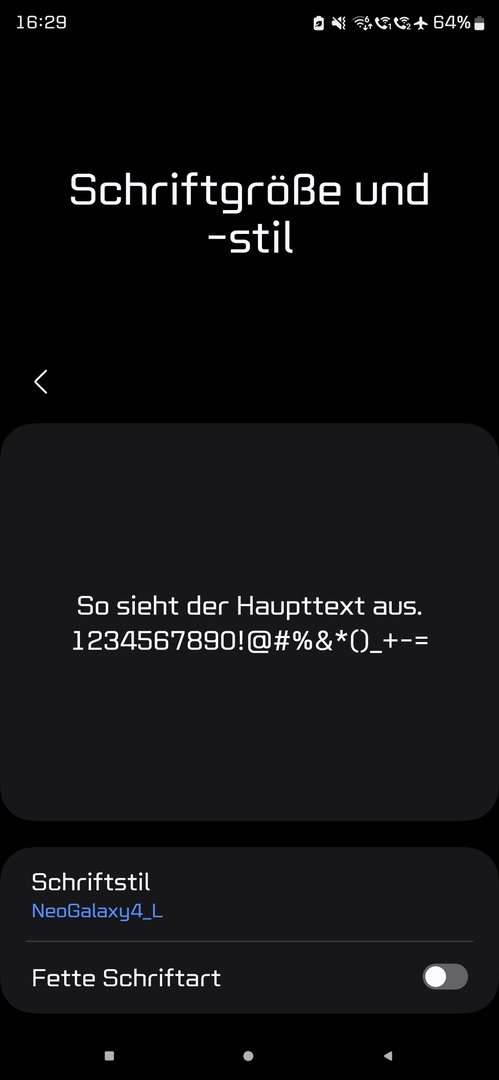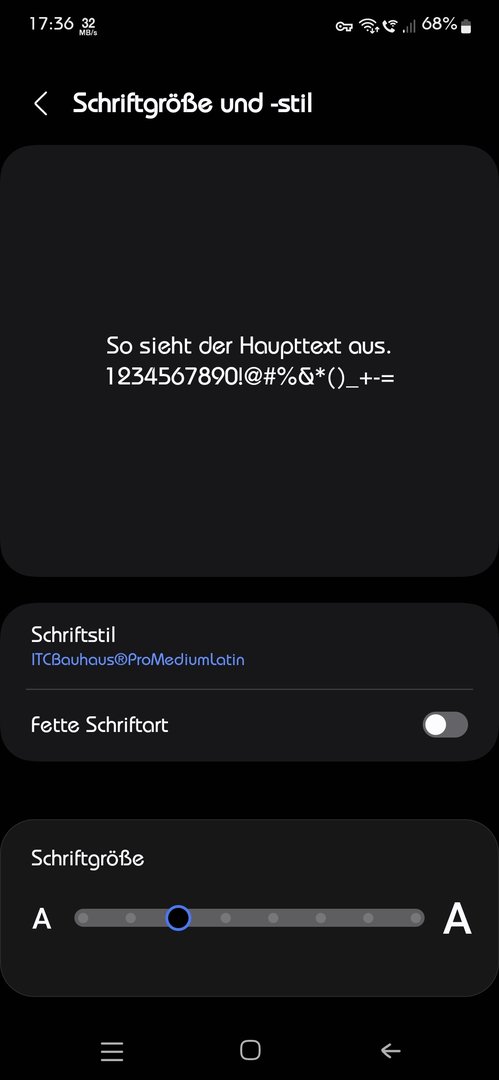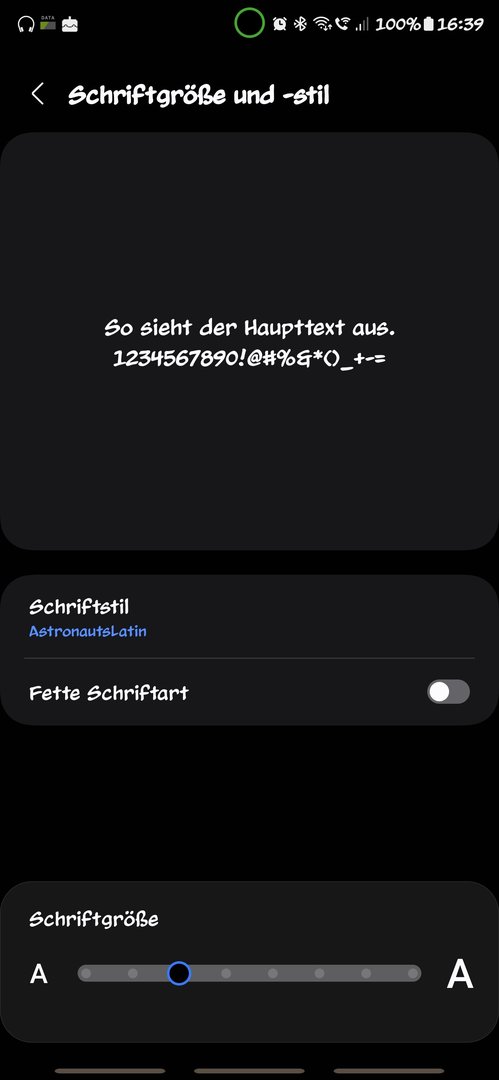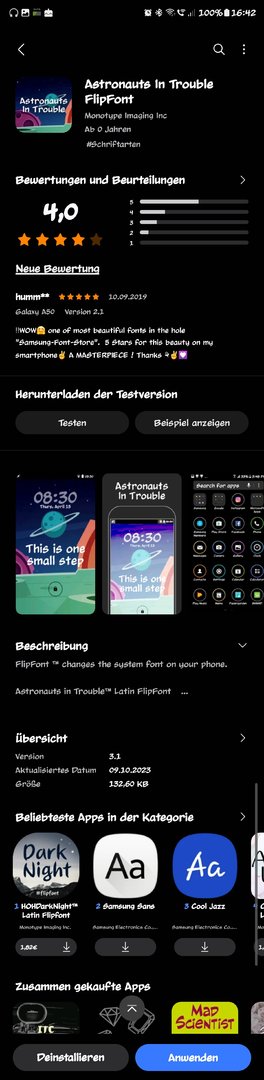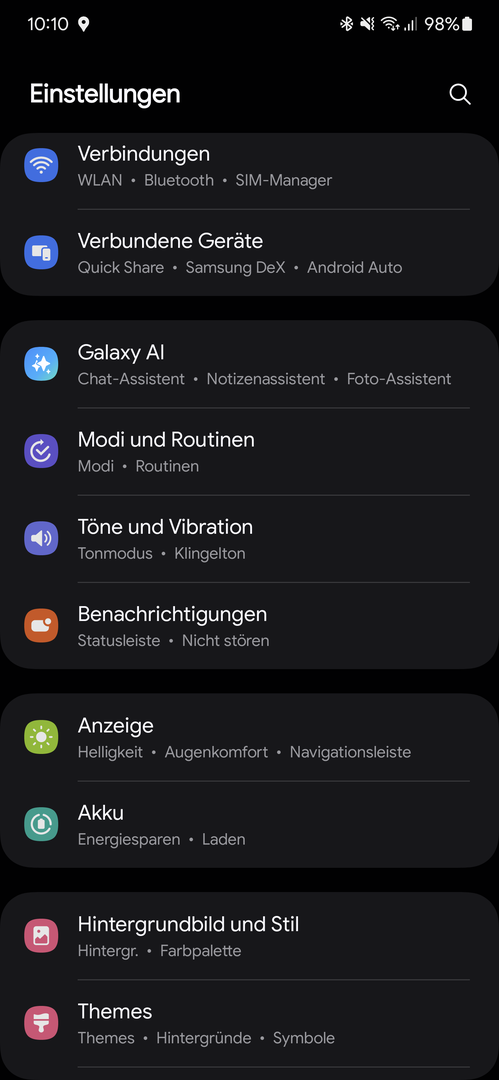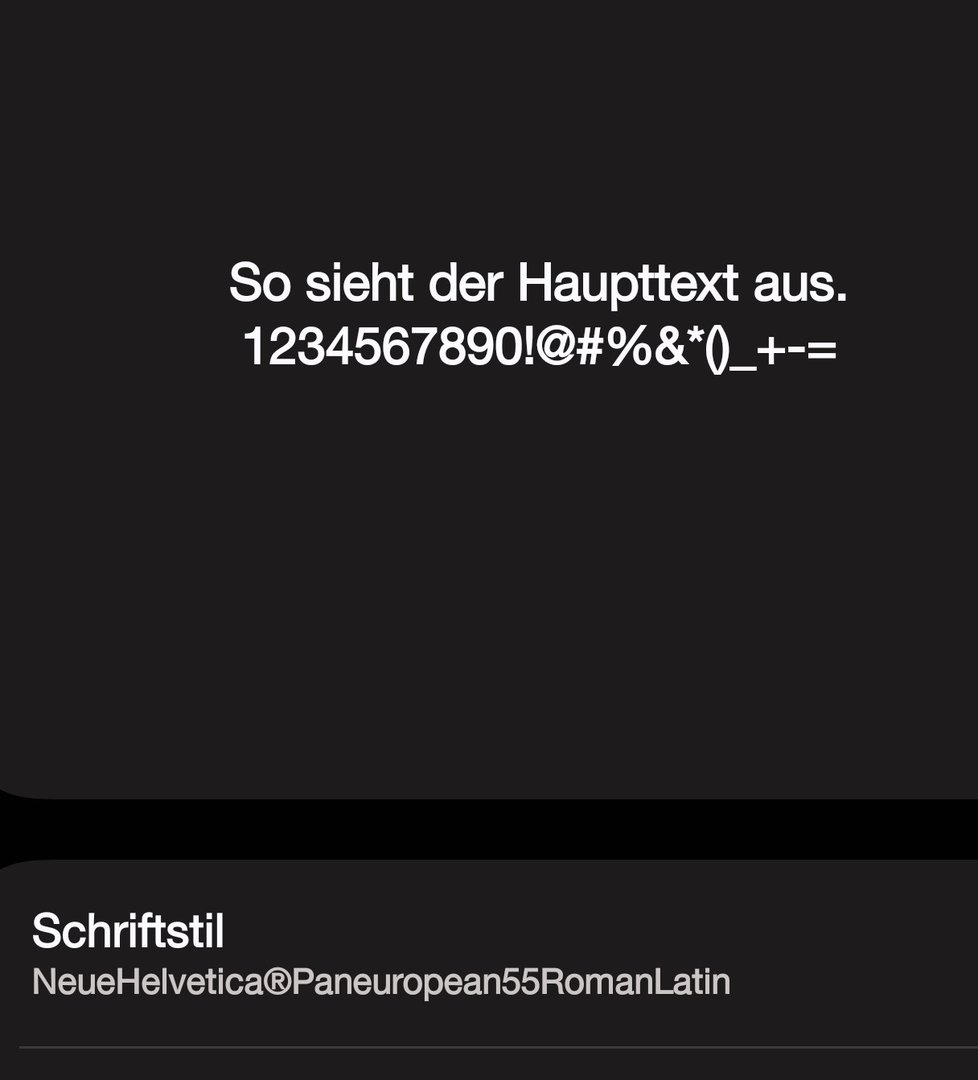
Welche Schriftart nutzt ihr?
Und noch eine, die auf Grund des Threads hier jetzt Snowwhite nutzt....
Hab mir die heute tatsächlich auch gekauft auf Grund dieses Threads 😀
Seit geraumer Zeit bin ich mit dieser unterwegs...
Ich nutze seit Jahren Bauhaus
Meine:
@Hennessy jap ich auch sieht auch gut aus:1f606:
Nutze schon seit vielen Jahren die Font
Astronauts in Trouble FlipFont
Seit ich denken kann nur GoogleSans, der Standardfont der Pixels. Mit Abstand die beste Lesbarkeit. Was anderes kommt mir nicht mehr aufs Handy. Gibt es natürlich nicht als Flip Font, weil Copyright bei Google...aber zFont regelt das 😉
Mein settings menu sieht genau so aus, nur habe ich nie den font geändert 🤔